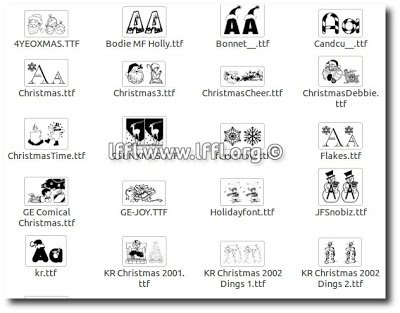
Raccolta di 55 Font dedicati al Natale (Linux - Windows - Mac)
Manca ormai pochi giorni al Natale, e molti di noi si appresteranno a preparare i biglietti per gli auguri. Perché non abbellirli con Font adatti al Natale? Su richiesta di molti lettori noi di LffL ne abbiamo raccolto ben 55 Font dedicati al Natale troveremo Lettere a forma di candele, addobbi pupazzi di neve e molto altro.